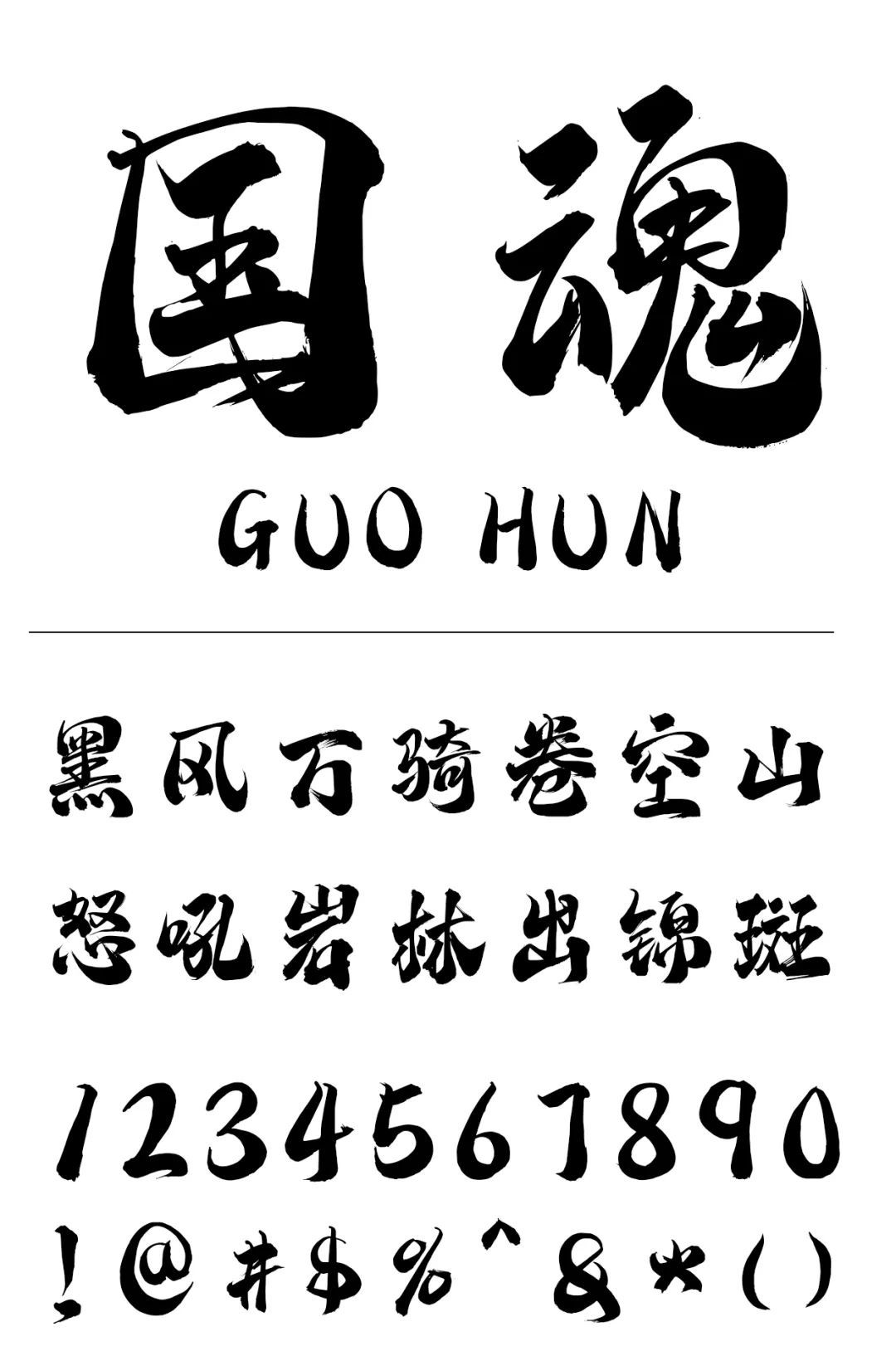
四月新字大盘点,本月我们上新了各种各样的字体,包括毛笔字体、创意字体、宋体等。这些字体都有其独特的特点和风格,可以让你的设计更加生动有趣。
1、印品国魂体
印品国魂体的笔画非常流畅,每一笔都非常细腻,让人感觉非常舒适。同时,它的笔画之间的转折处处理得非常到位,让字体显得更加自然。
2、三极虎啸体
三极虎啸体笔画造型别出心裁,刚硬锐利,带有狂放的肌理笔触。以尖角收笔,特点突出,浑厚洒脱,磅礴之感在笔尖肆意挥洒。
3、三极灵动体
三极灵动体:结构飘逸,充满手写的活泼动感。笔画由细入粗,以圆笔结尾,形似音符,粗细对比强烈。整体字形圆润、流畅有弹性,俏皮可爱。
4、字语文稚体
字语文稚体添加了高光元素字形圆润饱满,笔画简洁流畅,单纯可爱。整体个性萌动,轻松自在。
5、上首晴竹体
上首晴竹体字体整体修长方正,简洁大方,笔画采用简单的几何形状,粗细一致,在一些笔画的结尾处添加了尖角作为修饰,使得字体简洁但又不失活泼,给人一种简洁清新,轻盈通透的感觉。
6、Aa觉醒黑
Aa觉醒黑 字形竖长,模仿板刷绘制的民国美术字设计一款创意标题黑体。平直粗重的笔画加上一些繁体字的异体写法,简约现代之中渗透复古气息。该字体拥有9哥字重,满足不同的设计场景需求。
7、字语文新宋
字语文新宋字体笔画圆润,减少了宋体具有相对锋芒修饰感,韵律节奏恰如其分,字形流畅,中宫放松,横竖笔画粗细比例合理。
8、三极小篆体
三极小篆体具有秦朝篆书风格,圆润均匀的线条,颀长的字形,再加上近似左右对称的结构,使文字呈现出篆书独有的韵味。
9、Aa飞鸟集
Aa飞鸟集软笔随性绘成的字样,清新明快、优美灵动,仿佛畅游天空的飞鸟,自由自在。
10、小熊冻冻奶
小熊冻冻奶字体是一款非常可爱的手写字体,其字体线条柔和而不失清晰,字迹笔画连贯显得干练而不凌乱,清新简明,给人一种轻松愉悦的感觉。